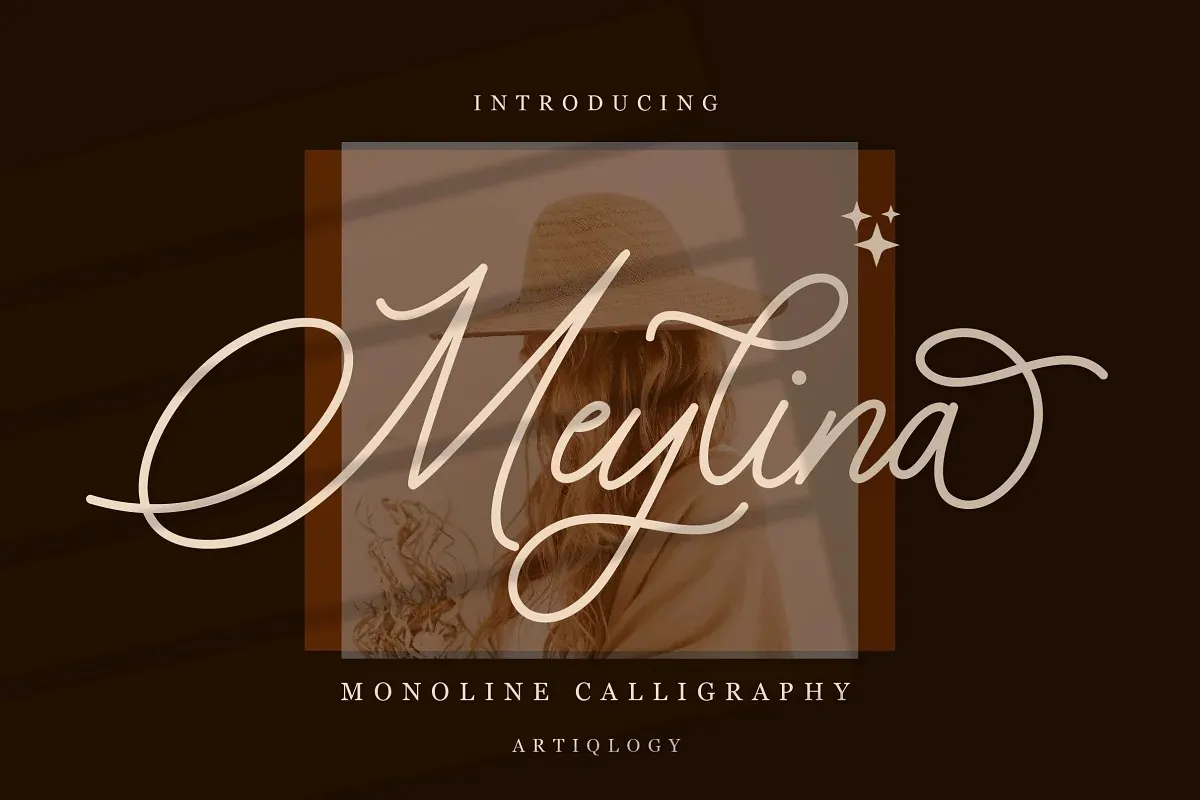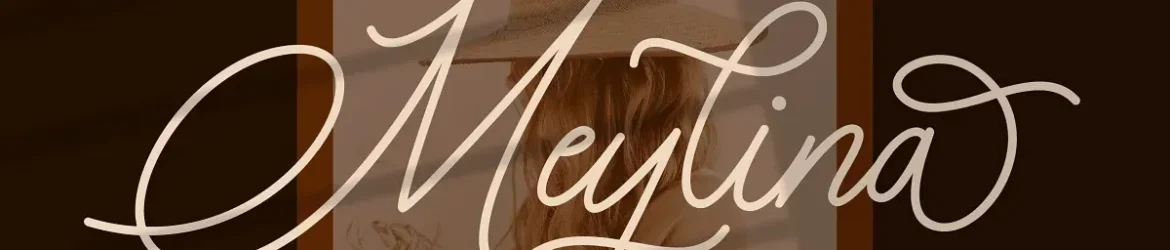
A Meylina é uma fonte script moderna, cheia de personalidade, criada pelo designer Artiqlogy para a plataforma 99designs. Suas linhas leves e elegantes permitem que você personalize textos de forma única, tornando-a perfeita para criar invitations de casamento incrivelmente belas, arte de cartões postais fascinantes ou postagens em redes sociais impecáveis. Com o uso do PUA Encoding, é simples acessar todos os símbolos e swashes desta fonte. Isso significa que você pode personalizar ainda mais seus projetos com facilidade, dando ao seu trabalho um toque único e sofisticado. Seja para criar cartões de felicitações elegantes ou postagens de rede social atraentes, a Meylina está sempre pronta para ajudar você a fazer o seu trabalho brilhar ainda mais.